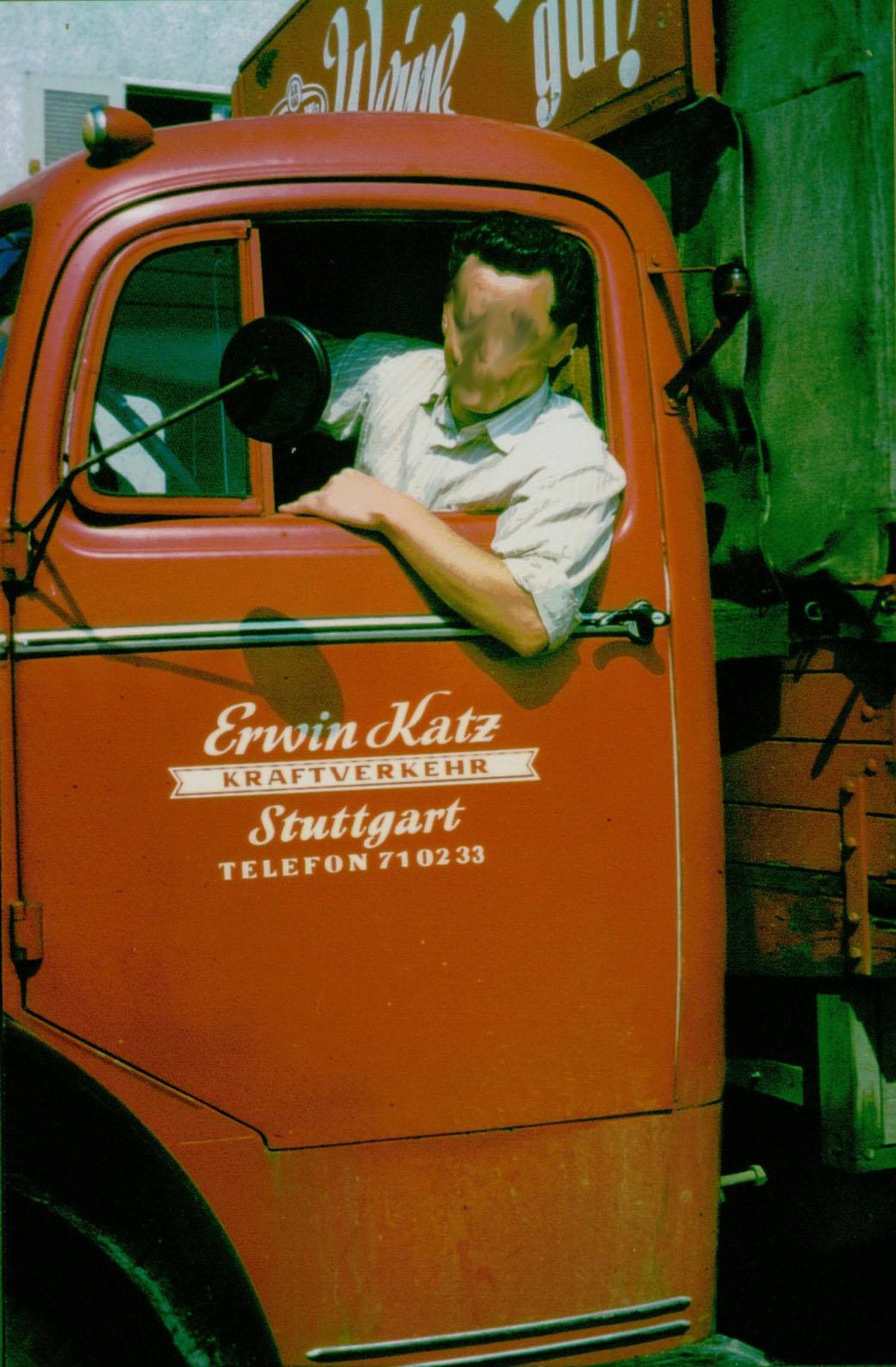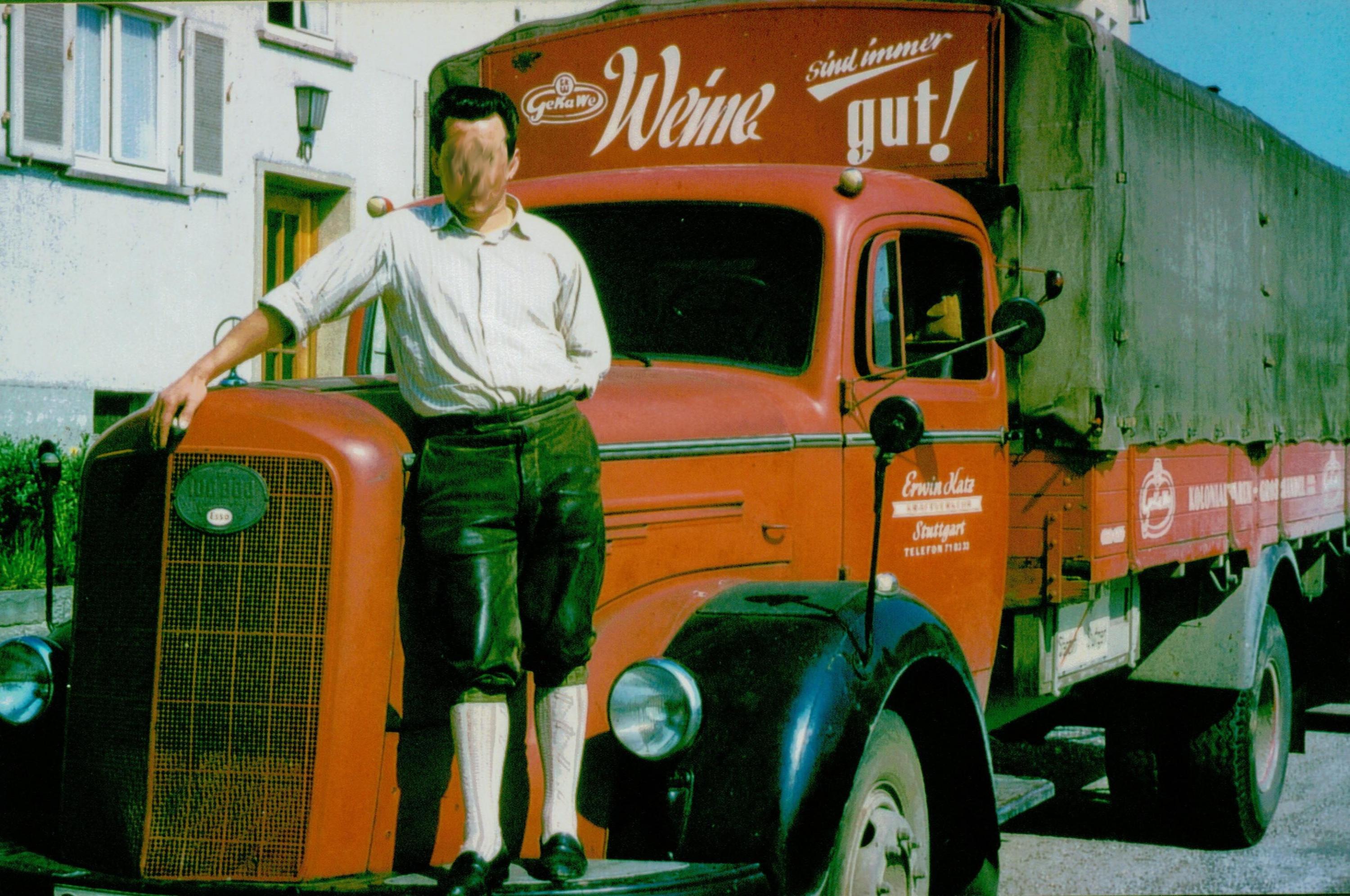
Suche Schriften auf dem LKW aus den 50er Jahren.
Wir haben den LKW aus den 1950er Jahren (vermutlich Anfang) als ferngesteuertes Modell nachgebaut. Die Firma war real existent. Die Person auf dem Bild auch (...die wird mit dem fertigen Modell überrascht). Wir möchten die Schriften plotten auf aufkleben. Jegliche Suche war bisher erfolglos. Es kann sein, dass der eine oder andere Schriftzug manuell erstellt wurde. Aber die Schriften auf der Tür dürften doch existierten? War kann helfen? Vielen Dank.Schriften_LKW1.thumb.jpg.fc18d5f85a7a3aee14933baa3bee9fc5.jpgSchriften_LKW2.thumb.jpg.19079228cf90df3015a9bc9ad7f8016a.jpg
Ähnliche wird es vielleicht geben, auf deinem Bild ist aber ein handwerkliches Werk zu sehen. Allein schon die 4 "t" in Stuttgart sind unterschiedlich.
Erst einmal:  (siehe unten)
Und dann habe ich diese Auto-Beschriftung aus der Zeirt vor Schneidplottern noch life bei den Lackierern in meinem Ausbildungsbetrieb gesehen. Das ging so:
Der Autraggeber hatte entweder einen Vorlage sich von einem Grafiker oder Schildermaler erstellen lassen, oder bei einfachen Texten machte dies auch der Lackierer, der eben auch die Vorlage von Hand zeichnete. Schriften zeichnen gehörte noch zur Ausbildung.
Dann wurde eine Stanniolfolie (sehr dünne Zinnfolie) mit Zuckerwasser auf die lackierte Tür geklebt, darüber dann mit Malerkrepp die Vorlage fixiert.
Mit einem Pausgriffel, das ist ein Stift, der an der Spitze eine winzige Stahlkugel sitzen hat, wurde dann die Vorlage in die Stanniolfolie durch eindrücken übertragen, anschließend wurden dann aus dieser Folie die Buchstaben mit einem Skalpel (Federmesser) ausgeschnitten und herausgepult, anschließend wurde die Beschriftung lackiert, und letztlich die restliche Fole entfernt. Bei mehrfarbigen Beschriftungen musste dieser Vorgang mehrfach widerholt werden.
Das war bis spät in die 1970er Jahre hinein alles manuell. Digitale Schriften gibt es jetzt etwa 35 Jahre. Mit Bleisatzschriften konnte man in diesem Zusammenhang rein gar nichts anfangen.
Ich weiß nicht, ob sich der Aufwand lohnt, das alles aus digitalen Schriften neu zu setzen und zu gestalten, zumal das Ergebnis ja bestenfalls ähnlich wäre. Die Vorlagen sind doch so gut, dass man daraus mit ein wenig Nachbearbeitung in Photoshop, Gimp o.ä. die Aufkleber für das Modell direkt generieren könnte.
Ich glaube schon, dass sich der Aufwand lohnt. Denn irgendwie muss die Schrift ja aufs Modell. Und es dürfte schon nicht einfach sein, aus den oben gezeigten Bildern eine »gerade« Photoshop-Version zu bauen. Dann muss das ganze auch noch vektorisiert werden, damit man es an einen Schneideplotter schicken kann. Zumal die Buchstabenabstände nicht ganz unproblematisch sind. Wie groß ist das Modell? Da wäre aus meiner Sicht die Vorgehensweise, die Beschriftung mit Fonts nachzubauen, wesentlich einfacher und technisch besser umzusetzen.
Danke für all diese Tipps! Der derzeitige Plan ist wirklich die Daten aus den original Bildern im Photoshop zu generieren. Alternativ ist der Gedanke, eine jeweils ähnliche  Plotterschrift zu modifizieren. Es wird noch dauern, bis das Modell lackiert und Beschriftungsbereit ist. Hier der Zwischenstand:
Ist das ein L 6600?